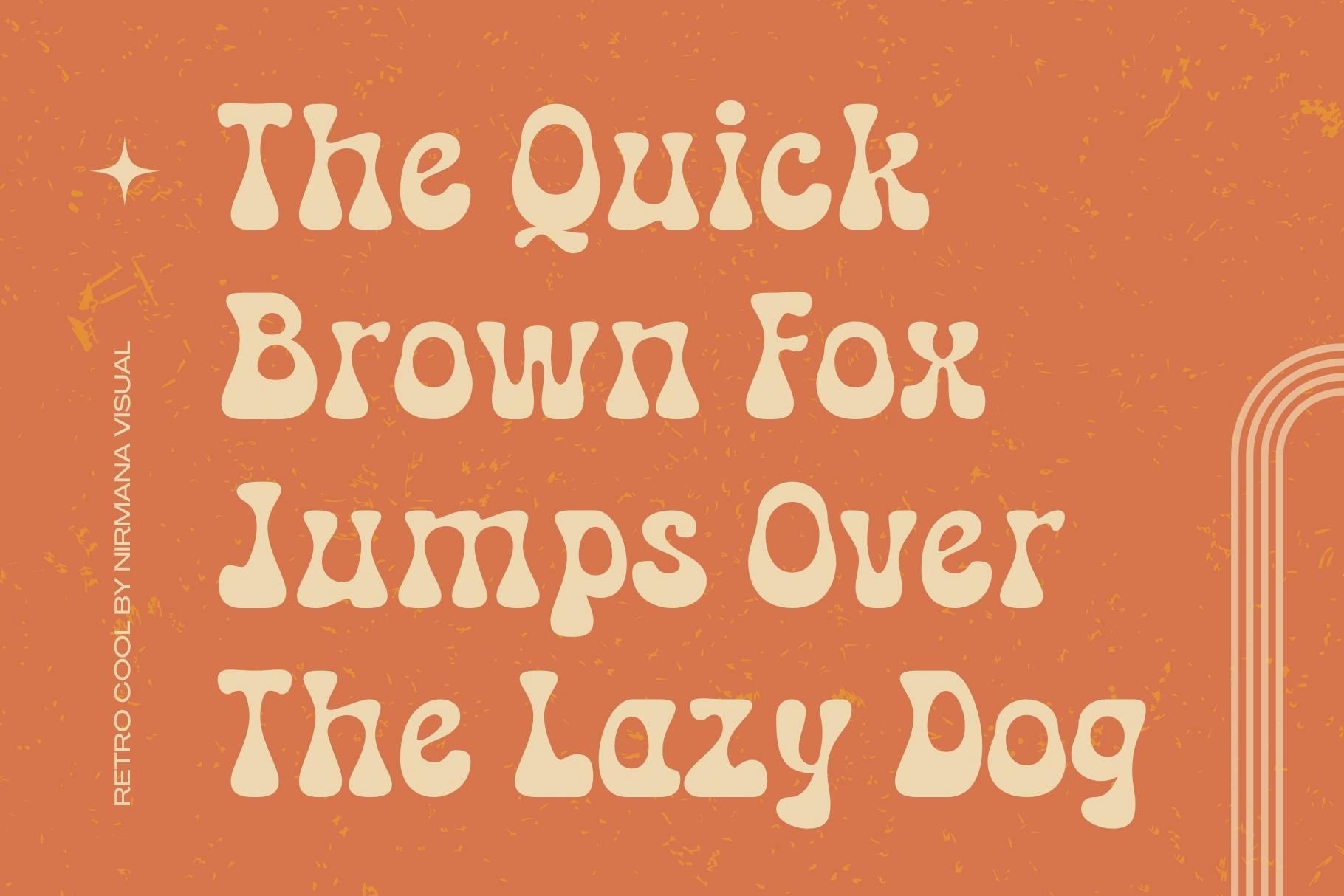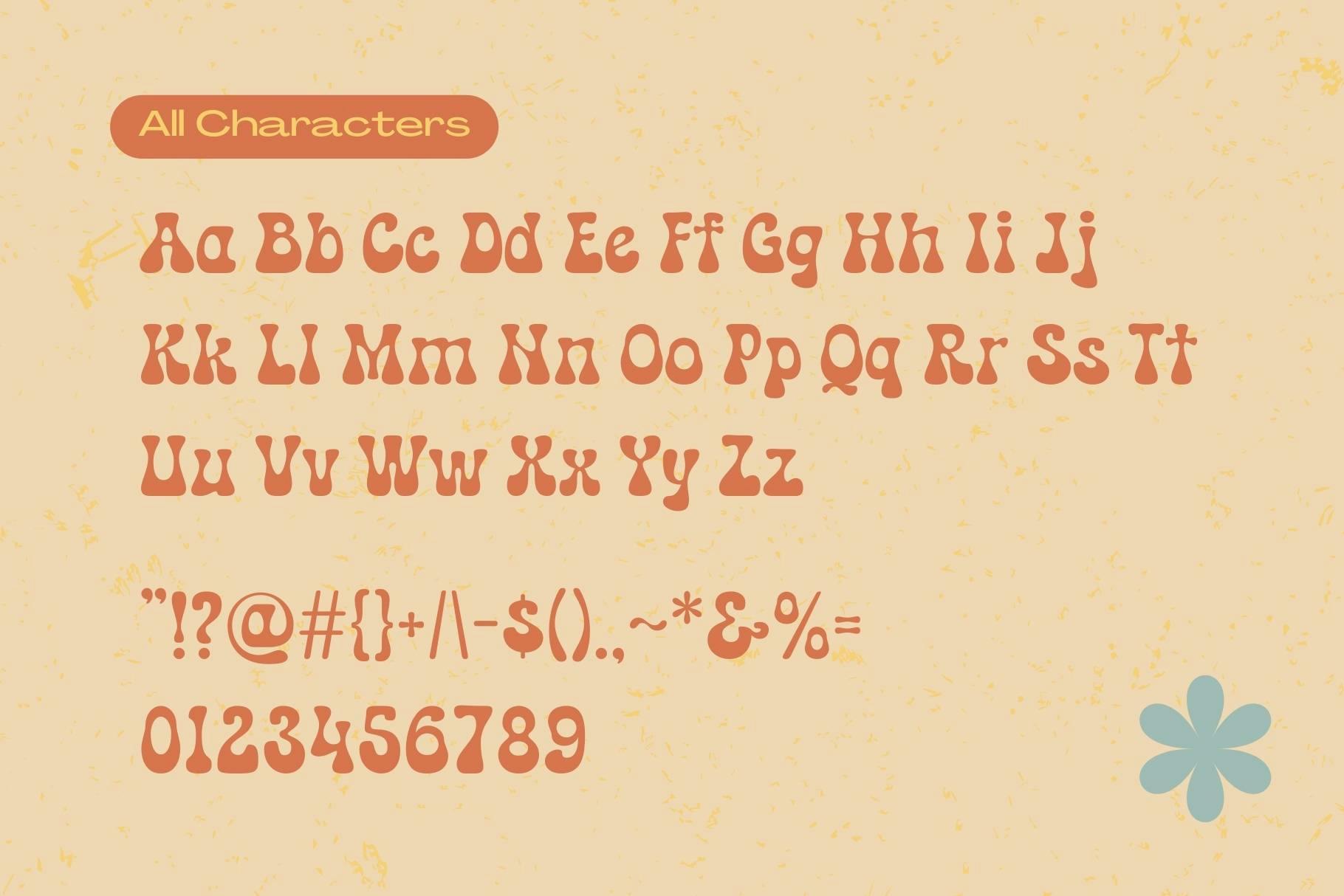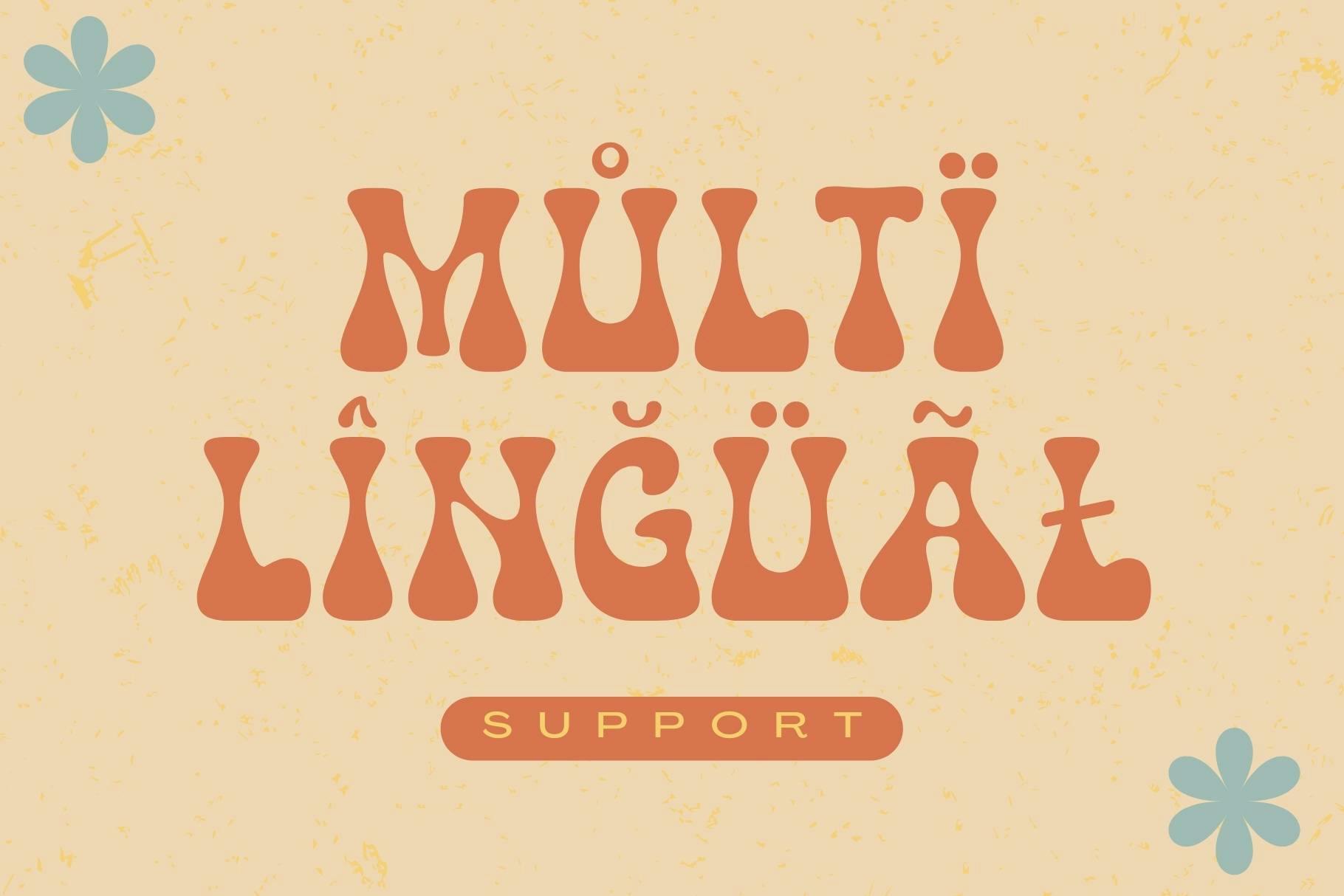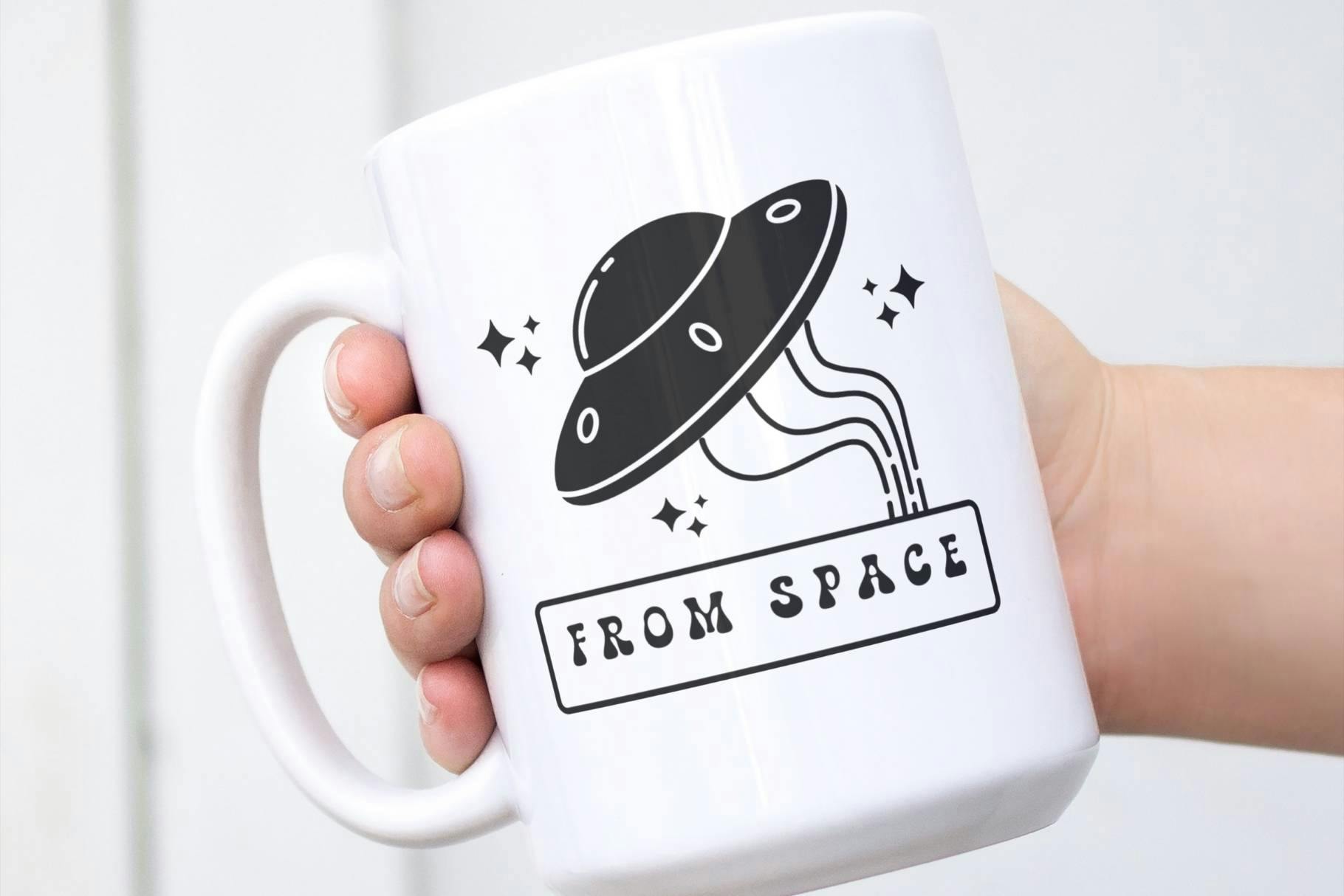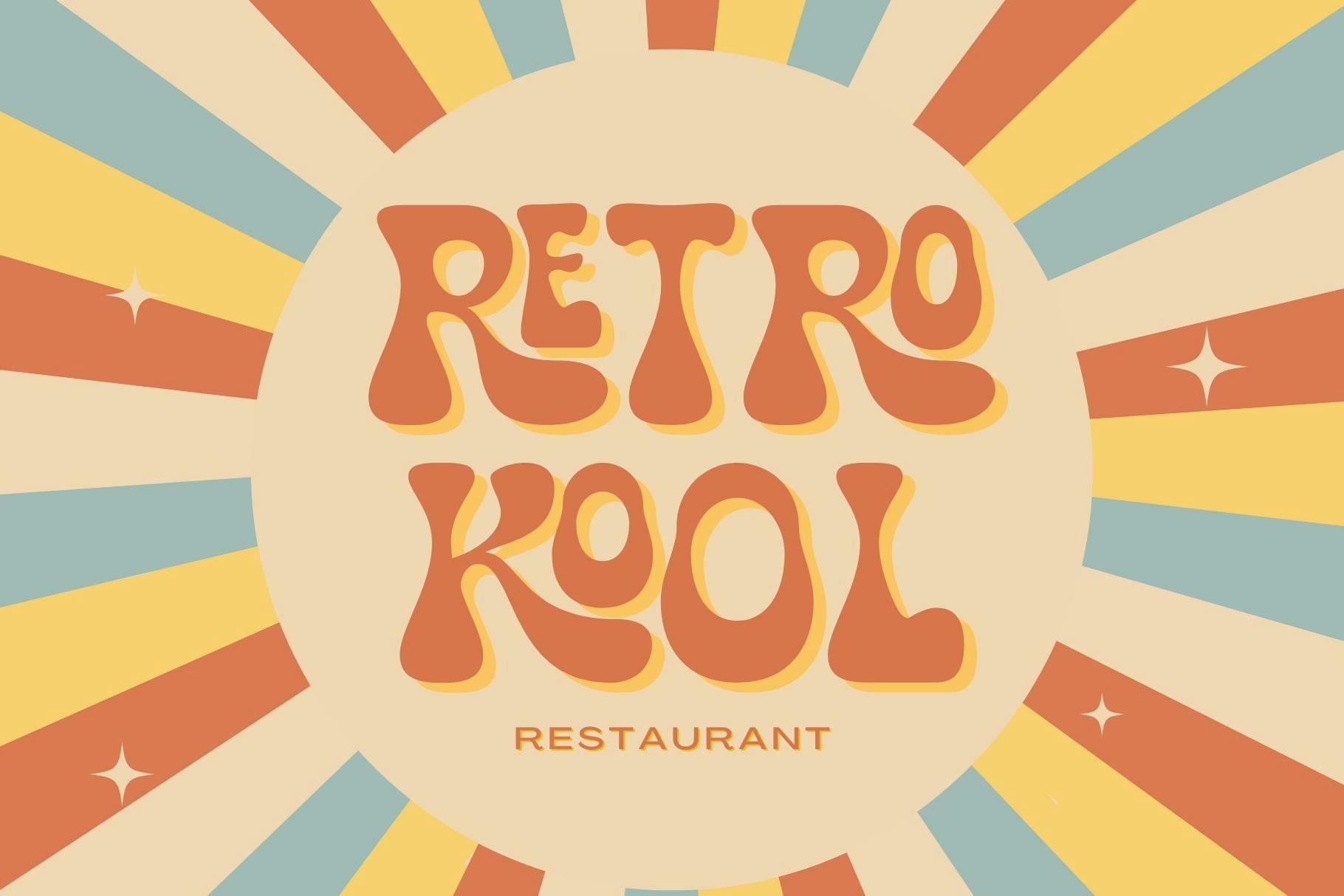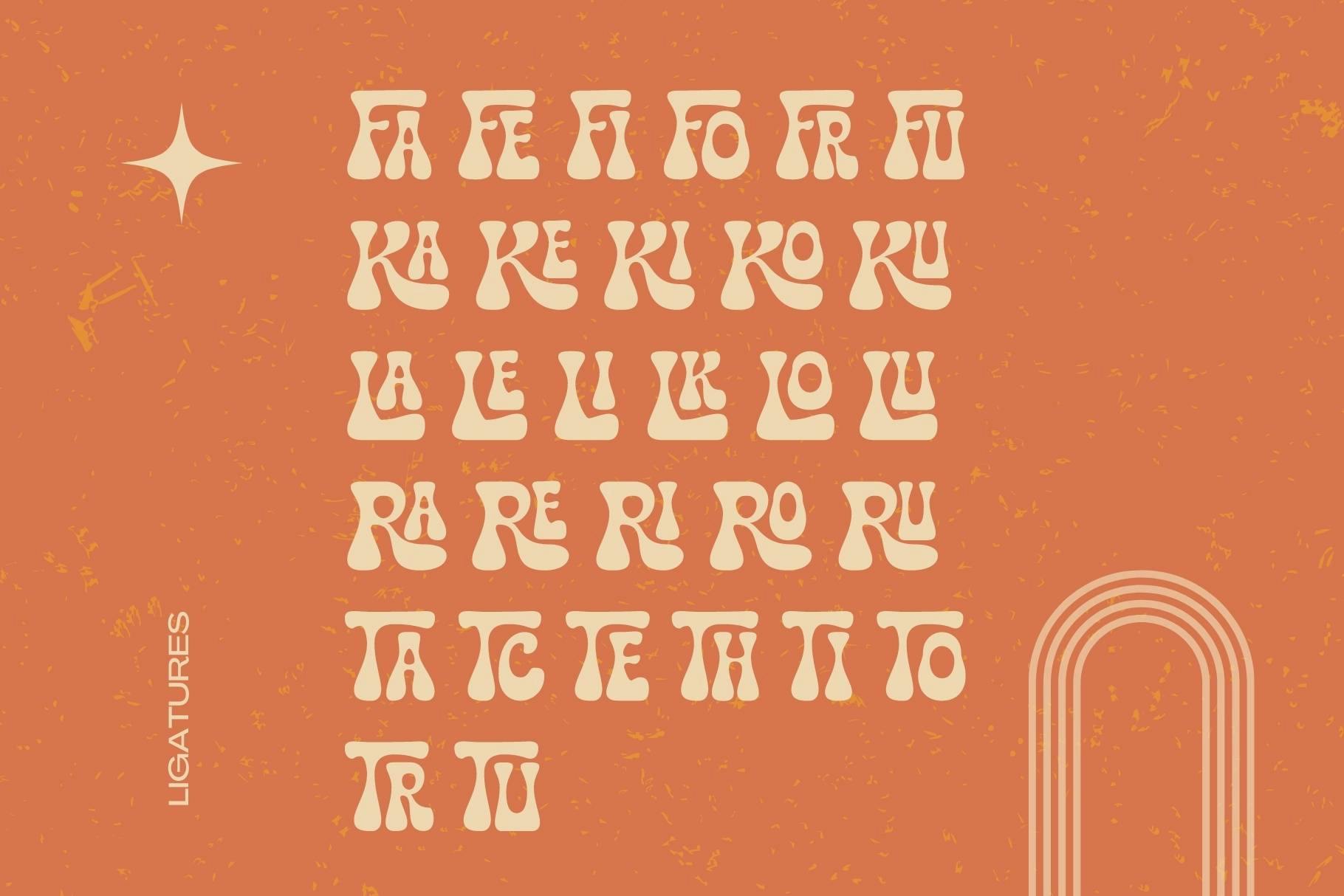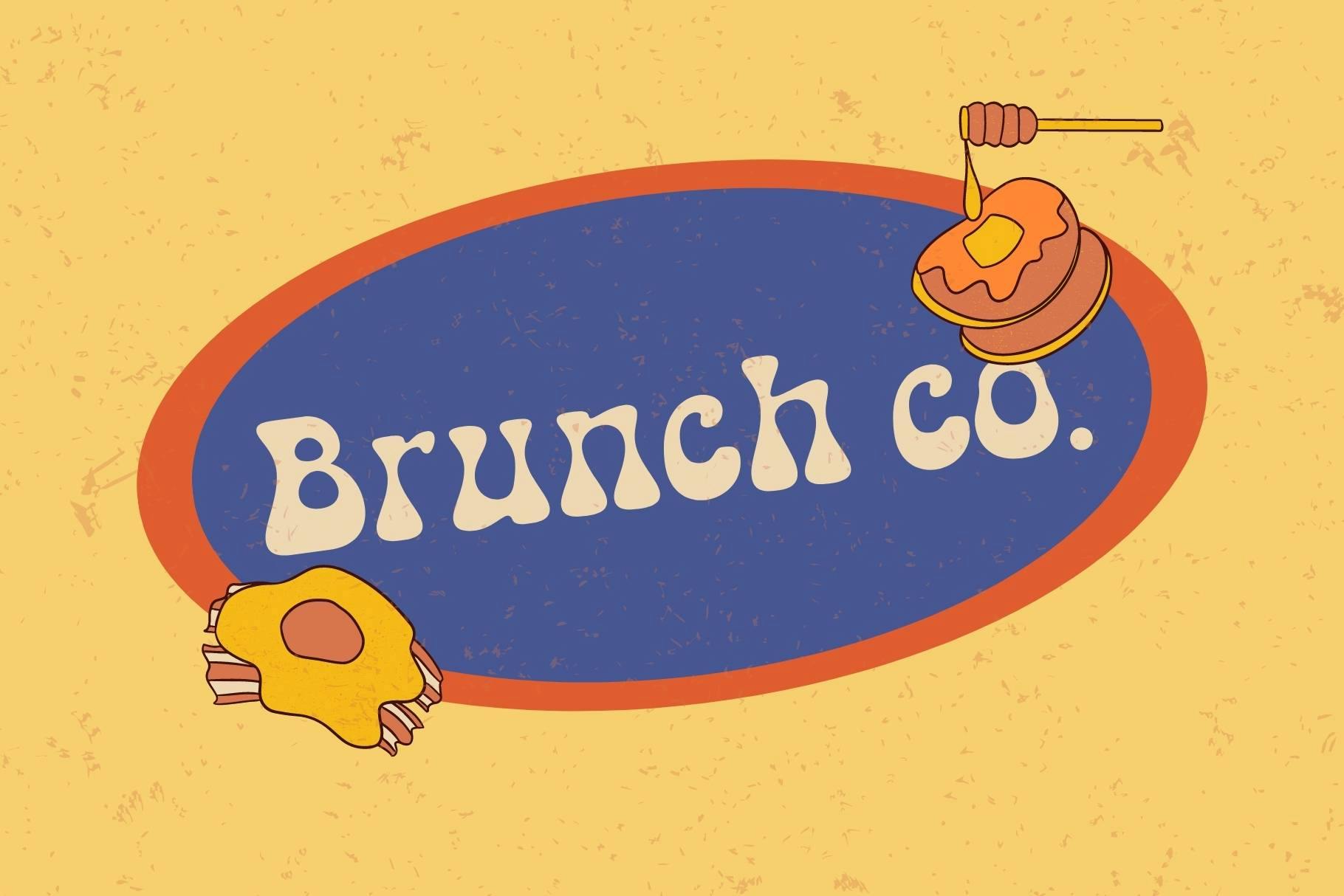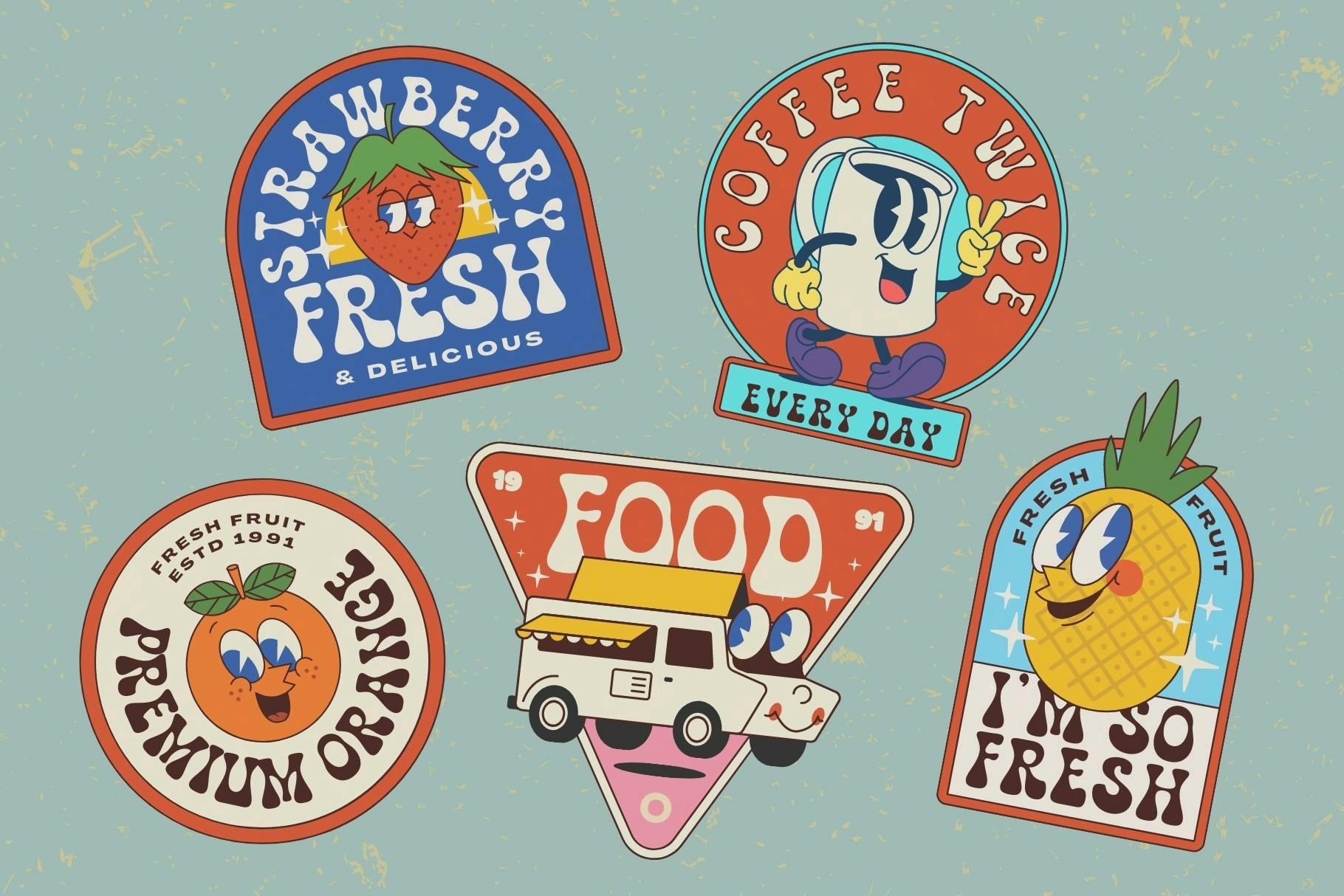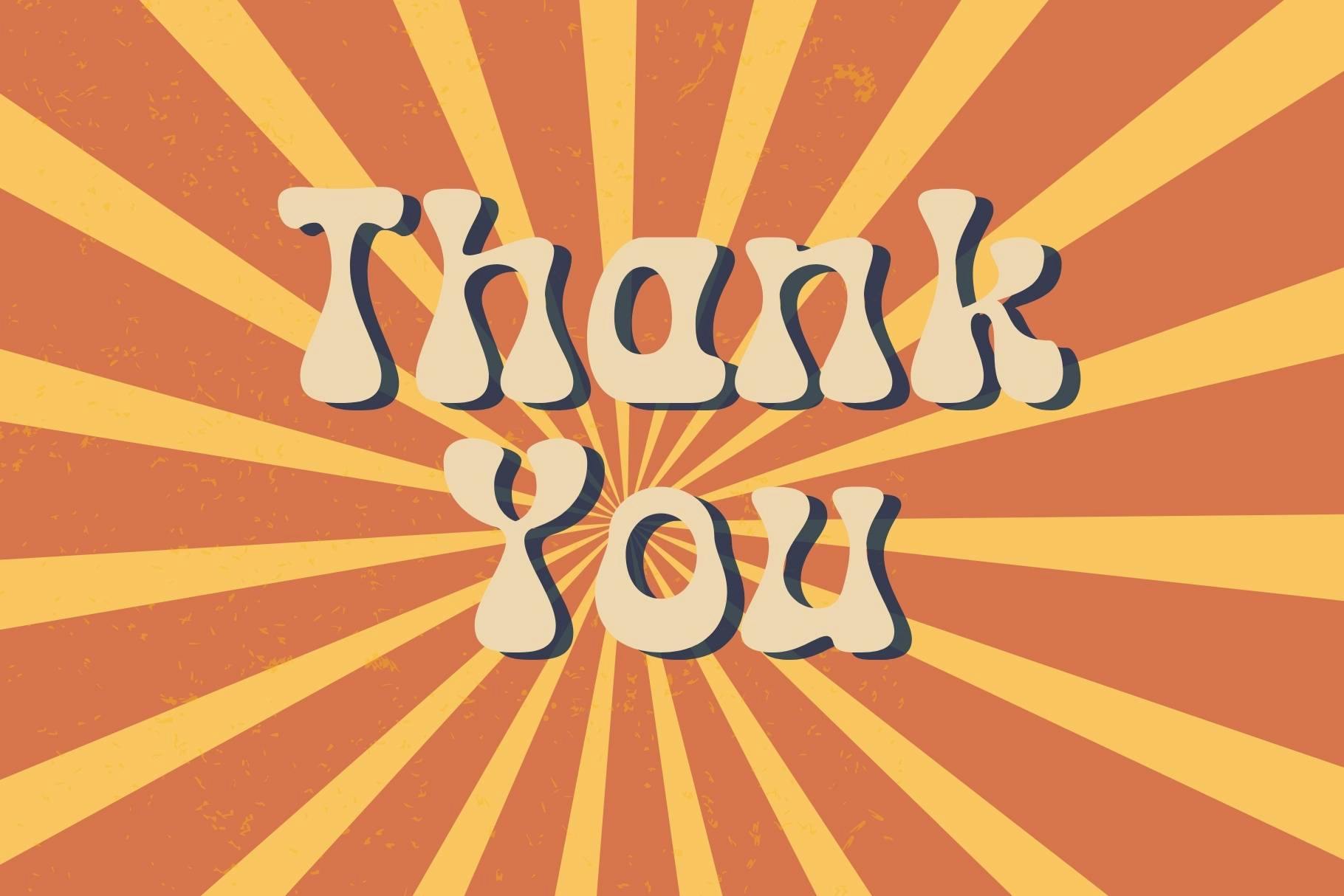
Retro Cool Logo Font
فونت ریترو کول، انتخابی ایده‌آل برای طراحی لوگو و برندینگ.
فونت ریترو کول، هم‌عصر فونت‌های سنس سریف،
ریتر کول زیبایی و هارمونی بی‌نظیری را برای پروژه‌های طراحی متنوع، از جمله لوگو و برندینگ، پست‌های رسانه‌های اجتماعی، تبلیغات و طراحی محصولات ارائه می‌دهد.